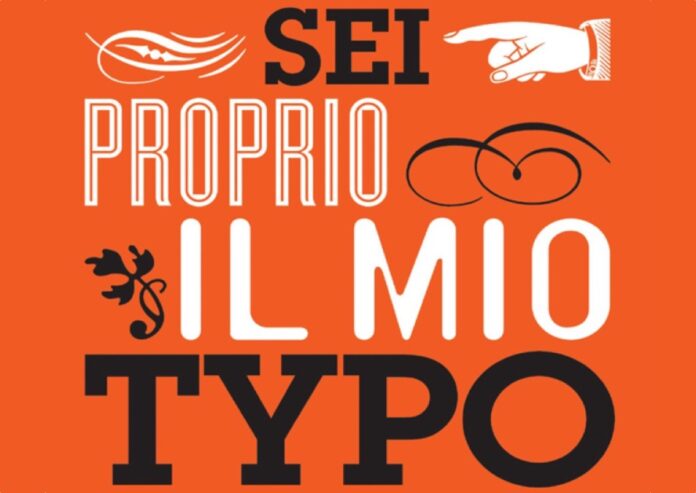
La pubblicazione in USA è stata una piccola rivoluzione: Sei Proprio il Mio Typo, il colto saggio firmato da Simon Garfield è già considerato un punto di riferimento per capire la storia di un aspetto molto particolare della tipografia.
Pressoché sconosciute fino a vent’anni fa, grazie all’avvento della tecnologia informatica oggi i font sono a tutti gli effetti protagonisti del nostro quotidiano. Ma quali sono state le tappe che hanno spinto i font a uscire dalla ristretta cerchia di addetti ai lavori e di qualche sparuto appassionato?
La risposta è in questo saggio di Simon Garfield, che rappresenta un autentico compendio della secolare storia della tipografia, da Gutenberg ai giorni nostri, che conta oltre centomila tra font e caratteri tipografici, ognuno con le sue peculiarità e le sue alterne fortune.
Condito di aneddoti sul design delle parole intorno a noi, Sei Proprio il Mio Typo si impone come testo di riferimento per quanti desiderano conoscere l’affascinante mondo dei font che, come sottolinea l’autore, non sono il semplice disegno di lettere dell’alfabeto, ma costituiscono un vero e proprio veicolo di emozioni.
E, come vedremo, è proprio in virtù di questa loro innata capacità comunicativa che, in molti casi, sono finite per diventare icone universalmente riconoscibili, scolpite per sempre, nel bene e nel male, nell’immaginario collettivo di ogni epoca e latitudine.